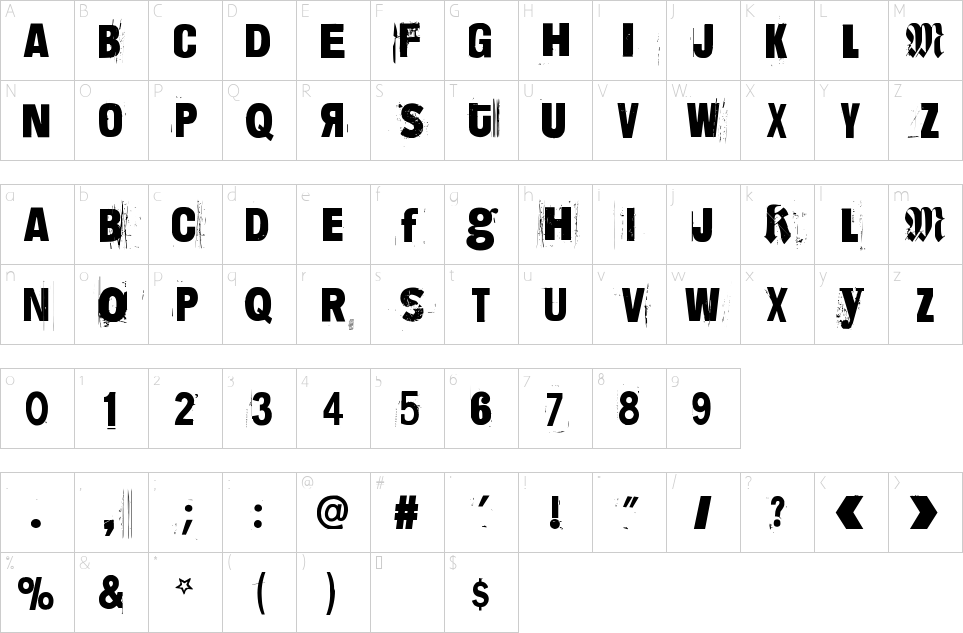
Descubra a elegância e a leveza do Dimension Zero Font, uma opção de graça para designers que buscam um estilo inovador em suas criações digitais. Especialmente adequada para uso em projetos gráficos modernos ou interfaces de usuário, esta fonte é resultado da criatividade singular de junkohanhero. Não apenas seu design distingue-se pela sua simplicidade e elegância, mas também por ser extremamente versátil – adaptando-se facilmente a diversos estilos de apresentação visual. Com o Dimension Zero Font, você ganha uma ferramenta poderosa para expressar a sua ideia de maneira única. É um download conveniente que vem em versões compatíveis com Windows e Mac, permitindo-lhe explorar suas potencialidades no seu ambiente de trabalho favorito. Seja para o design de sites, editoração de textos ou criação de materiais digitais de alta qualidade, o Dimension Zero Font é uma escolha inteligente que enriquece a sua coleção de ferramentas gráficas.